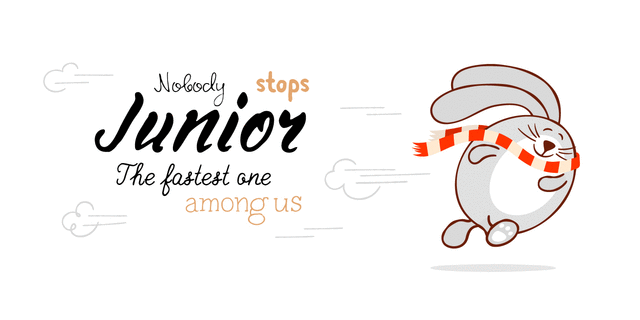
TT Rabbits – сверхэмоциональное рукописное шрифтовое семейство, состоящее из 10 разных шрифтов. Мы объединили эти шрифты по одной общей теме – детство. Используйте эти шрифты для создания любой продукции для детей – детские книжки, приложения для детей, интерьеры детских комнат.
Мы дали каждому кролику уникальное имя. Имена выстроены по буквам латинского алфавита: A — April, B — Bro, C — Chilli, D — Dummy, E — Elf, F — Fatso, G— Goody, H — Hyper, I — Idol, J — Junior. Каждый кролик имеет свой характер, поэтому вы определенно полюбите TT Rabbits. Мы использовали индивидуальный пишущий инструмент для каждого шрифта. Все шрифты изначально создавались на бумаге, а затем оцифрованы.
А какой ваш любимый кролик? Шрифт разработан Иваном Гладких в студии TypeType Fonts в 2016 году.
Ассоциации c семейством TT Rabbits JКачества и характер:
быстрый, артистичный, органический, динамичный, свежий, неряшливый, веселый, сладкий, легкомысленный, современный, эмоциональный, жидкий, лихой, подвижный, непоседливый, ягодный, фруктовый, мультяшный, яркий, вкусный, смешной, добрый, наивный, милый, мягкий, ремесленный, рукотворный, ручной, домашний, уютный, семейный, экологичный, дружелюбный, доверительный, зеленый, натуральный, природный, аппетитный, здоровый, игривый, забавный, прикольный, живой, оригинальный, приветливый, характерный, праздничный, сочный, спелый, крафтовый, радостный, озорной, весенний, летний, кустарный, самодельный, приятный, няшный, вежливый, счастливый, артизанальный, небрежный, проворный, вернакулярный, бегущий, свободный
весна, кафе, компот, дача, интерьер, цветы, подарки, семья, варенье, джем, сладости, конфеты, мармелад, конфитюр, базар, зоомагазин, зоопарк, животные, детская книжка, каникулы, хенд мейд, еда, отдых, лавка, десерт, праздник, день рождения, фрукты, овощи, природа, сок, анимация, мультфильм, закуска, фаст фуд, торговля, булочная, утренник, соус, развлечения, пицца, юмор, котики, селфи, школа, хюгге, дерево, кетчуп, чипсы, инстаграм, графика, иллюстрация, дом Стилистика: